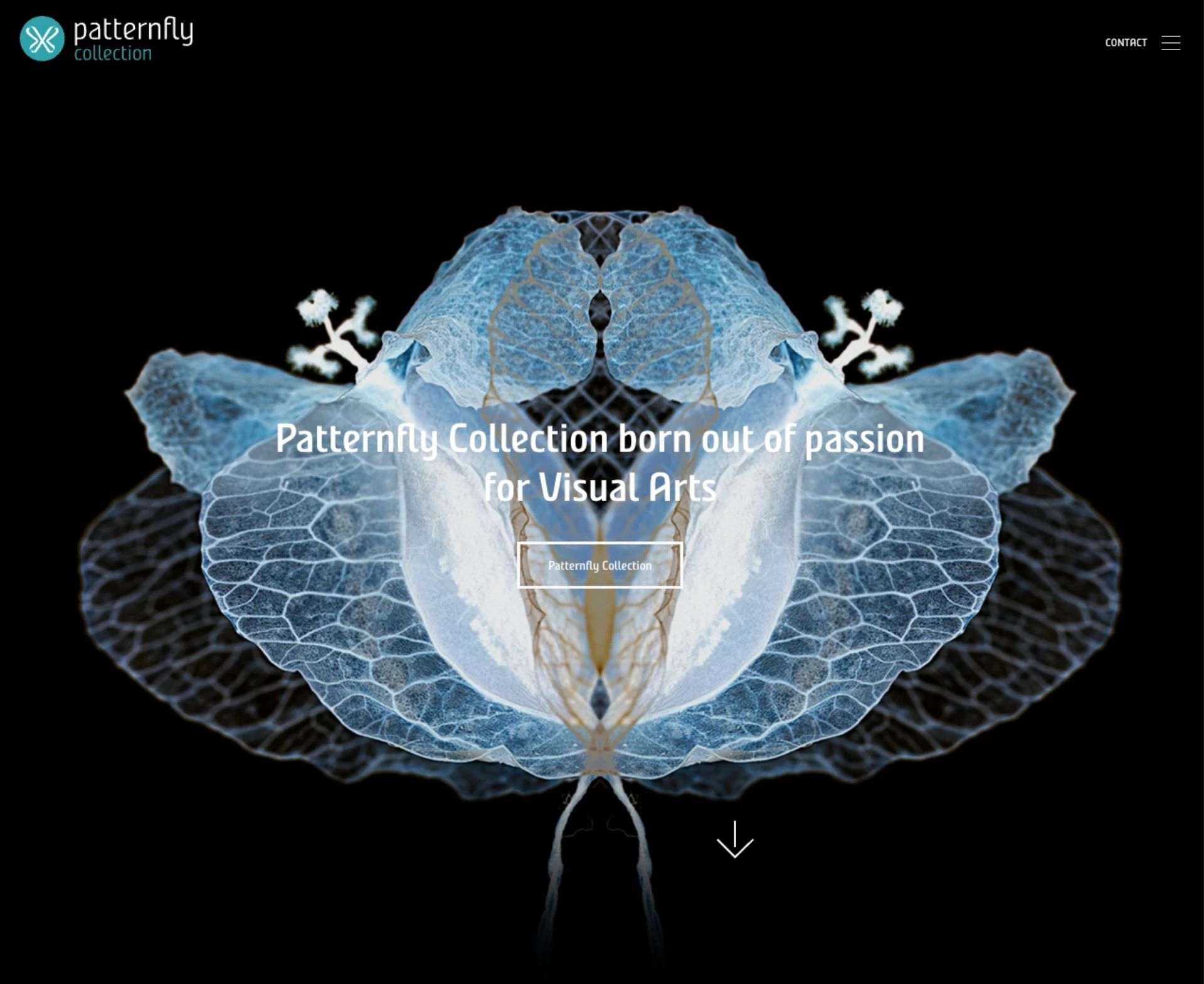
Nordic Narrow – coolness of the North
Nordic Narrow is een stoer en modieus lettertype met een Scandinavisch tintje. Het heeft 14 stijlen voor de hardcore ontwerper. Nordic Narrow heeft zijn basis in een geometrisch grid, maar weet toch een warme analoge flair te behouden. Een van de kenmerken is de diagonale middellijn. Het schittert in mode-, tijdschrift- en logo-ontwerpen.
Nordic Narrow gewichten en stijlen
Nordic Narrow Pro heeft maar liefst 14 stijlen (7 gewichten plus bijpassende echte cursief) en draagt 391 lettertekens (glyphs). Een cool werkpaard voor zowel stoere ontwerpers als typeliefhebbers.
Nordic Narrow in use
Wij hebben de Nordic Narrow font familie vaker voor onze eigen opdrachten gebruikt. Van klanten als ‘De vrouw van de voetballer’ tot ‘Vocale Workshop’ en vele print media uitingen.
Internationaal hebben veel designers de Nordic Narrow gebruikt. Van Conincx Pop uit Elsloo tot het Melissa magazine uit Spanje en de Signaler Expositie uit Noorwegen.
Het Nordic Narrow font is een cruciale factor voor het onderscheidend vermogen van de branding.
Hier een aantal voorbeelden van Nordic Narrow in gebruik:
OpenType features
Nordic Narrow bevat veel elegante OpenType features voor een soepele toepassing op de verschillende platforms en media. Til je corporate branding naar een hoger niveau met deze uitgebreide font familie.
- Discretionary Ligatures
- Fractions
- Numerators
- Oldstyle Figures
- Ordinals
- Standard Ligatures
Taalondersteuning
Nordic Narrow ondersteunt 96 Latijnse talen. Kijk of het de jouwe spreekt. Laat het ons weten als je meer talen nodig hebt.